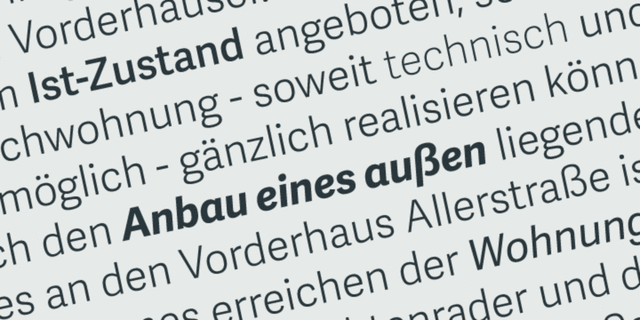
Adelle Sans – это гротесковый аналог отмеченной наградами гарнитуры Adelle. Он предлагает более энергичный взгляд на традиционные гротески. Как обычно бывает в TypeTogether, при проектировании Адель Санс мы учли все самые важные качества шрифта для редакционных материалов. Сочетание живого характера и незаметного внешнего вида, присущего гротескам, делают его совершенно универсальным средством для любого применения, от текста до логотипов, вывесок и рекламы. Без всяких сомнений, главное качество Адель Санс – это гибкость.
Адель Санс доступен в семи вариантах насыщенности с соответствующими курсивами. Каждый из этих 14 начертаний идеально соответствует по весу и пропорциям своему эквиваленту с засечками. Это обеспечивает хорошее сочетание между обоими семействами шрифтов в одном блоке текста с тонким, но заметным изменением текстуры при использовании в одинаковом кегле.
Шрифт содержит 900 символов и включает все типографские тонкости, капитель, несколько наборов цифр, а также поддержку более 90 языков. Таблица символов также содержит набор из 35 иконок, специально предназначенных для электронных изданий.
Шрифт разработан Вероникой Буриан и Хосе Скаглионе и выпущен студией TypeTogether в 2012 году.
13-е из 14 начертаний
Функции начертания Adelle Sans HeavyПрименение в макете:
Ассоциации c начертанием Adelle Sans HeavyКачества и характер:
точный, деловой, устойчивый, стабильный, статичный, твердый, серьезный, ровный, прямоугольный, железный, стальной, надежный, уверенный, сильный, индустриальный, техногенный, убедительный, авторитетный, внушительный, мощный, тяжелый, военный, армейский, мотивирующий, ответственный, суровый, громкий, крутой, качественный, амбициозный, умный, рабочий